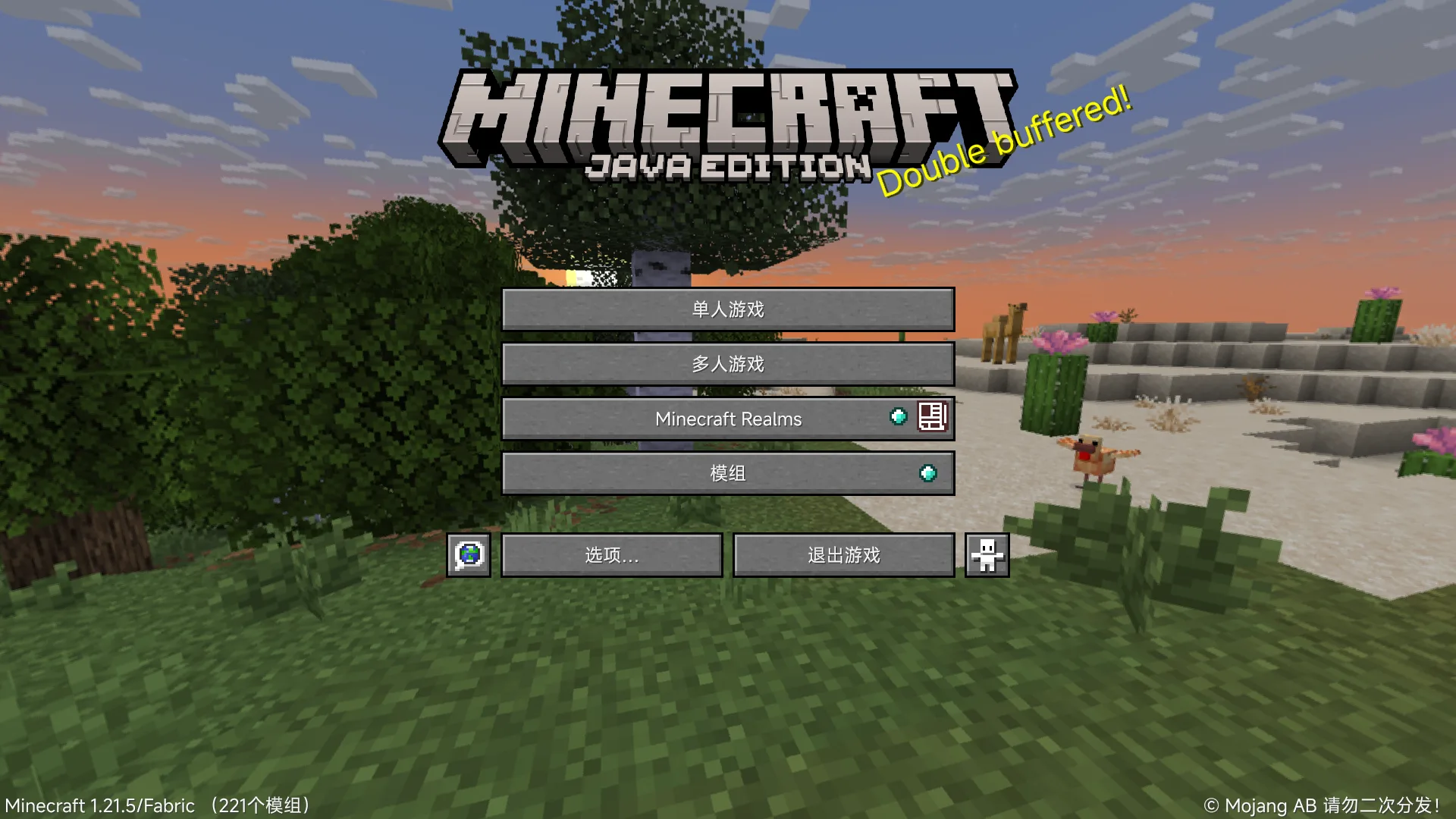
MiSans Font
MiSans Font — это ресурспак, заменяющий стандартный шрифт Minecraft на MiSans для улучшения визуального восприятия. Для работы требуется мод Caxton.
Ресурспак MiSans Font заменяет стандартный шрифт Minecraft на MiSans, предлагая более чистый и современный вид текста в игре. Это улучшает читаемость и общую эстетику интерфейса, создавая приятную атмосферу.
Основная особенность — это новый опыт работы с текстом в Minecraft, делающий игру визуально более привлекательной. Ресурспак фокусируется исключительно на замене шрифта, без дополнительных изменений в графике или геймплее.